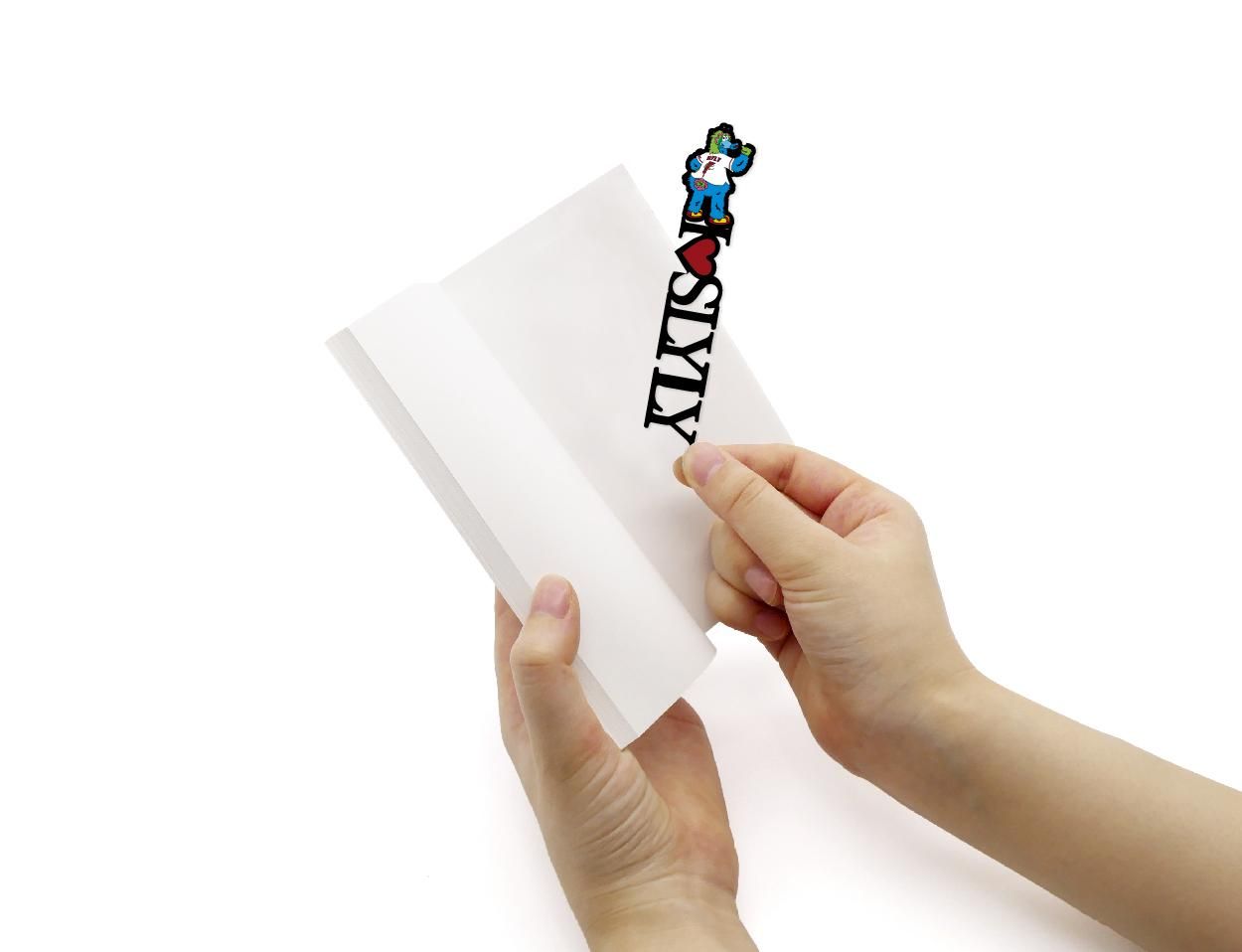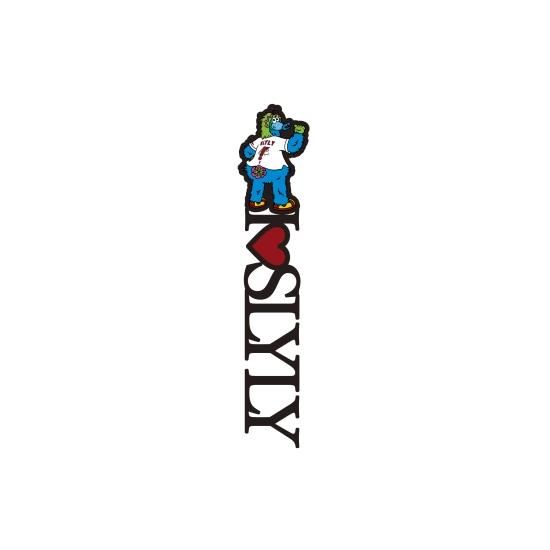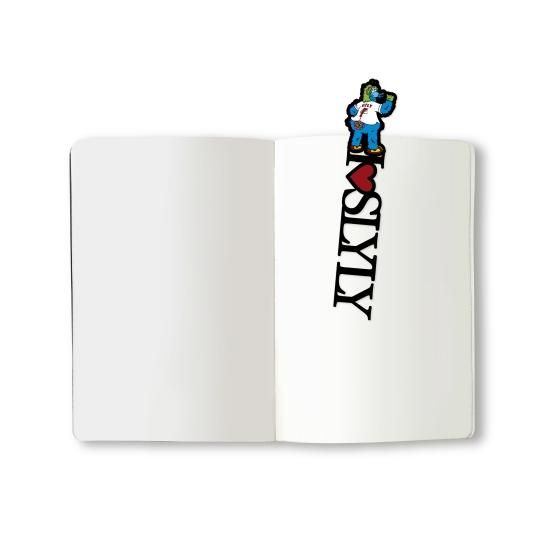
文字のカープのしおり「I♥SLYLY」
カープへの想いが、突き抜けたら『文字のカープのしおり』になりました。
ファンの気持ちをストレートに表現した言葉にのって、スラィリーが本や手帳の上でも大活躍!
推しをはさんで、推しとともにカープな日々をお過ごしください。
木材パルプや綿を原料とした環境素材を採用し、耐久性・耐水性に優れたファイバー紙の特徴を活かすことで、
言葉がフォントごと切り取られたような巧緻で美しい『文字のしおり』のデザインが実現しています。